中国的文字博大精深,中国文字的书法也是需要一定技巧的。虽然现在网络很发达,但是还有很多人对于文字书法存在着一种很深的感情。或许大部分人并不了解文字书法,但是文字书法的确能展现中国文化的博大精深,那么大家对于文字书法到底了解多少呢?如果不了解的话,下面就一起来看一看文字书法的相关信息吧!
篆书书法分为大篆和小篆,是一种取之相应的文字,虽然现在很少使用,但是仍有很多人学习,为了方便一些篆书字体爱好者的学习,印品字库特意创作了一款适合现代人使用的篆书字体-印品篆遇简。因为篆书书法现在是一种艺术。篆书保留了象形文字的特点,是秦国的通用文字。篆书整体刚劲有力,笔触瘦劲挺拔。整体结构看起来也比较简洁,但是篆书的线条比较多,书写起来比较麻烦。
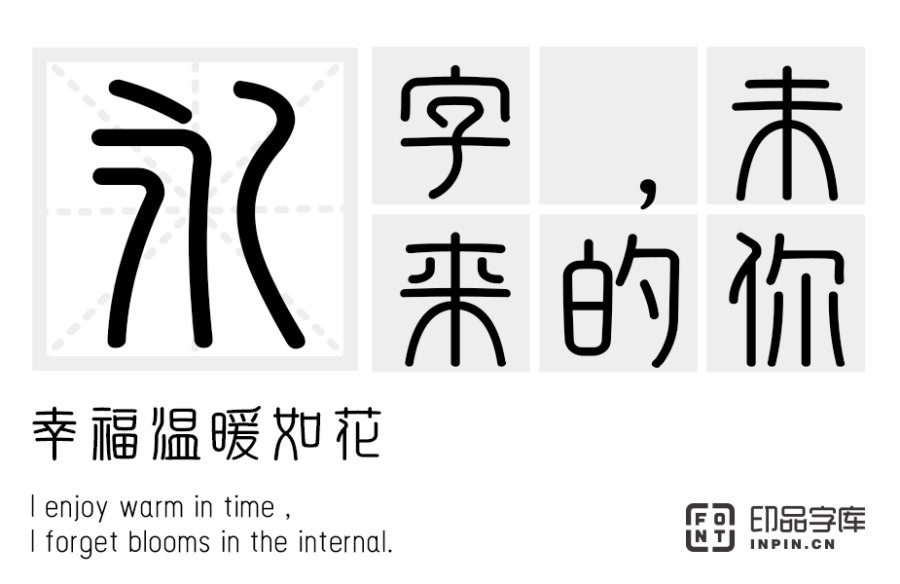
行书虽然是在隶书的基础上发展起来的,但是它是却是一种介于楷体和草书之间的字体,行书的出现也算是弥补了楷书和草书的缺点。行书有很多属于自己的特点,它不如隶书方,也不如篆书圆,它的字体结构与还是有些相似,但它的书写速度要比楷书快很多。
草书出现在汉代,是汉代最常用的一种字体。草书的书写速度很快,但它的整体结构比较抽象,所以一般情况下很难让人看懂。不过草书是具有艺术字体性质的,它整体风格比较飘逸,相对来说比较符合现代人的审美。